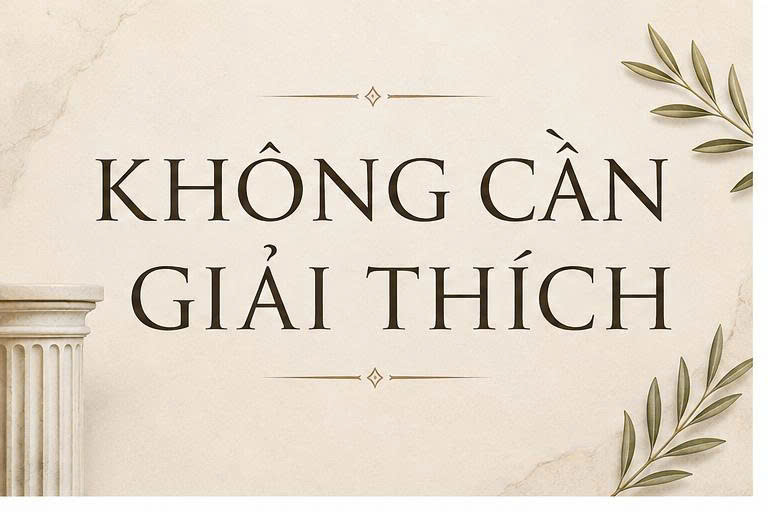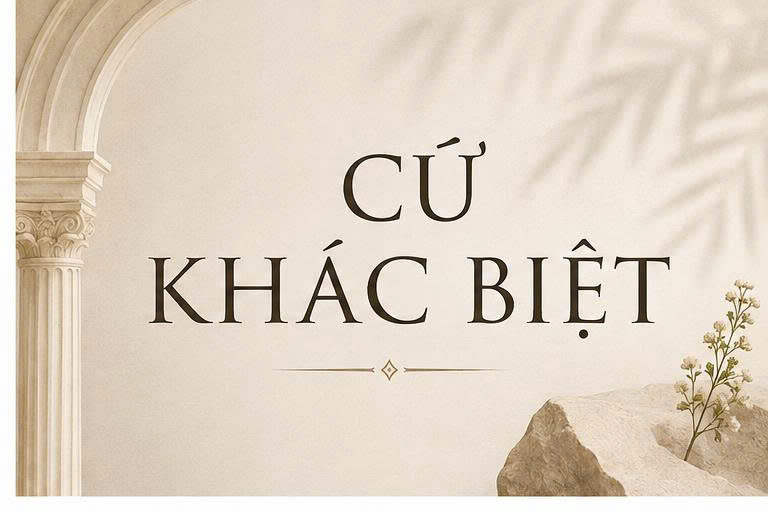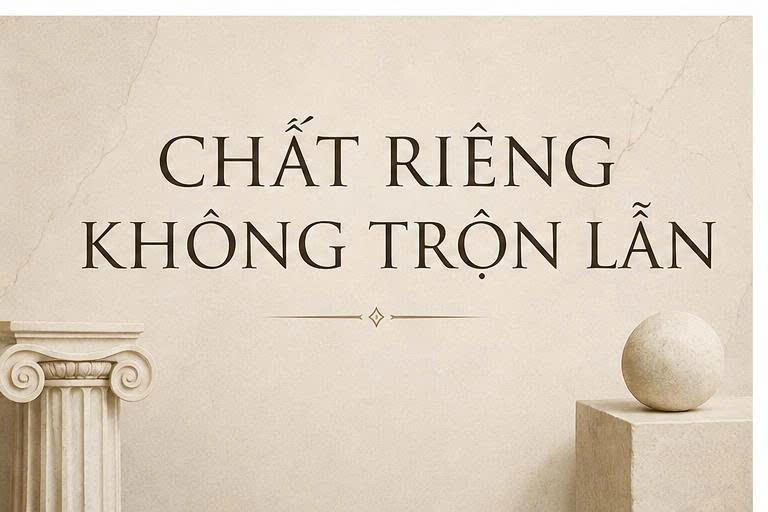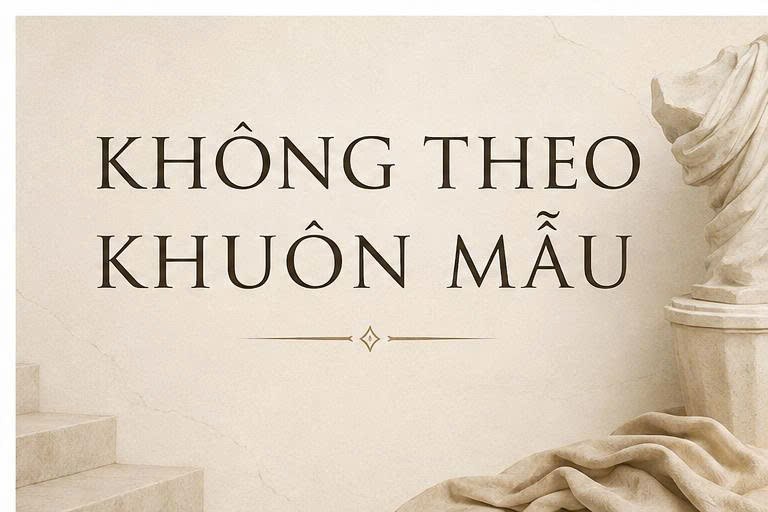
Đặc điểm thẩm mỹ của font Trajan Pro Việt hóa
Trajan Pro không đơn thuần là một bộ phông chữ; nó là sự tái hiện linh hồn của nghệ thuật điêu khắc cổ đại trong dòng chảy đồ họa hiện đại.
Phong cách La Mã cổ điển và uy nghi
Đặc trưng lớn nhất của font Trajan Pro Việt hóa là cấu trúc chữ dựa trên tỷ lệ chuẩn mực của các cột đá La Mã thế kỷ thứ II. Các đường nét thanh mảnh nhưng chắc chắn, kết hợp với phần chân (serif) sắc sảo tạo nên một diện mạo vô cùng trang trọng. Đây là bộ font lý tưởng để truyền tải thông điệp về sự bền vững, uy tín và giá trị vượt thời gian của thương hiệu.
Cấu trúc chữ in hoa (All-caps) chuẩn mực
Trajan Pro được thiết kế chủ yếu ở định dạng chữ in hoa (Small Caps), nơi các chữ cái thường có hình dáng tương tự chữ in hoa nhưng kích thước nhỏ hơn. Đặc điểm này giúp phông chữ giữ được sự đồng nhất và tạo nên nhịp điệu Typography vô cùng sang trọng, rất phù hợp cho các tiêu đề chính hoặc tên thương hiệu đặt ở vị trí trung tâm bao bì.
- Giải quyết lỗi hiển thị tiếng Việt: Việc tải font Trajan Pro Việt hóa chuẩn giúp các dấu thanh (sắc, huyền, hỏi, ngã, nặng) được đặt ở vị trí tinh tế, hài hòa với cấu trúc chữ gốc, không làm mất đi vẻ thanh lịch của font.
- Tạo dấu ấn đẳng cấp Hollywood: Sử dụng Trajan Pro giúp bao bì sản phẩm của bạn mang hơi hướng điện ảnh và nghệ thuật cao, dễ dàng thu hút sự chú ý của phân khúc khách hàng cao cấp.
- Tính ứng dụng trường tồn: Dù qua nhiều thập kỷ, Trajan Pro vẫn không hề lỗi mốt, luôn giữ vững vị trí trong các thiết kế đòi hỏi sự chuẩn mực và sang trọng tuyệt đối.